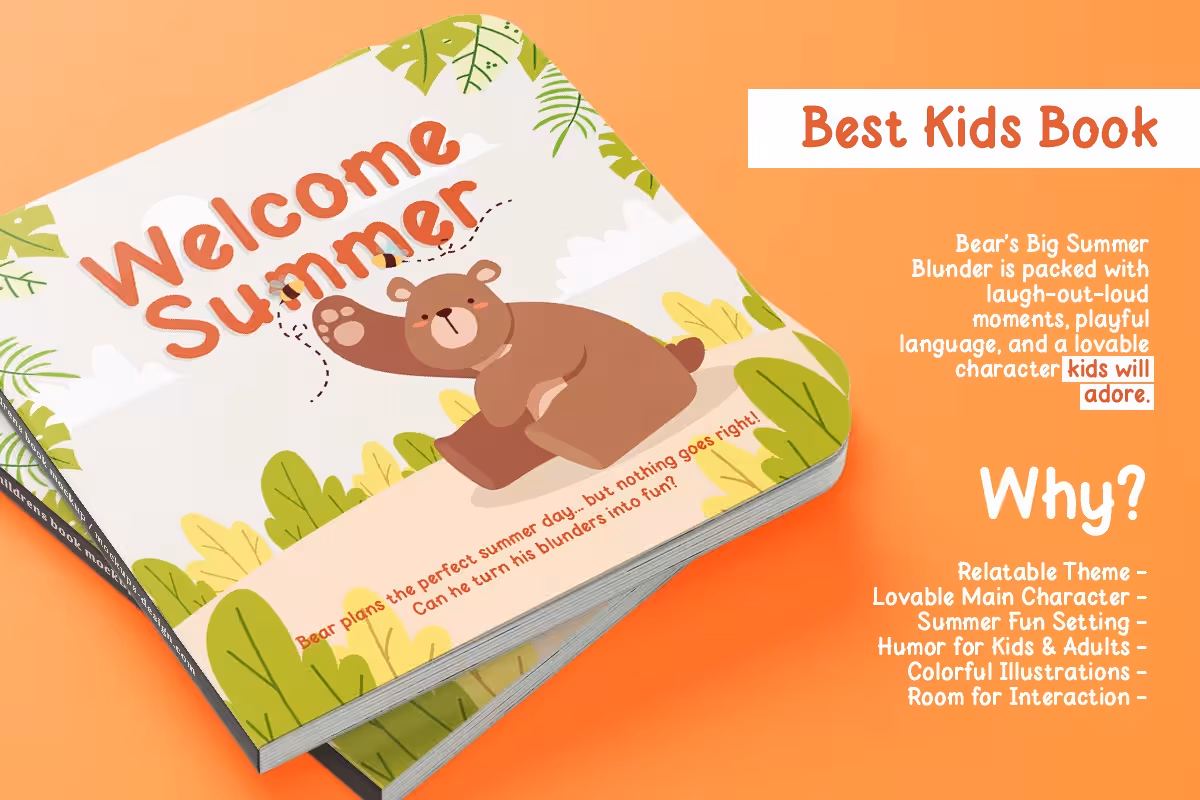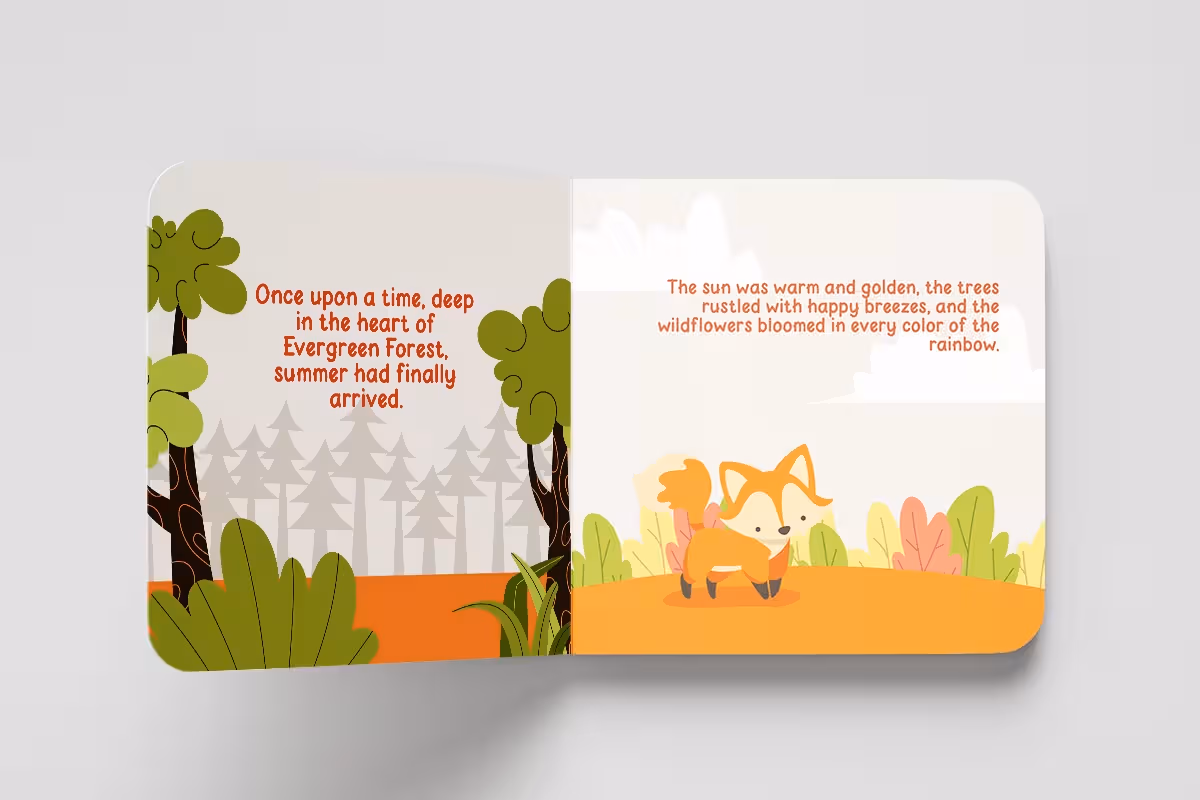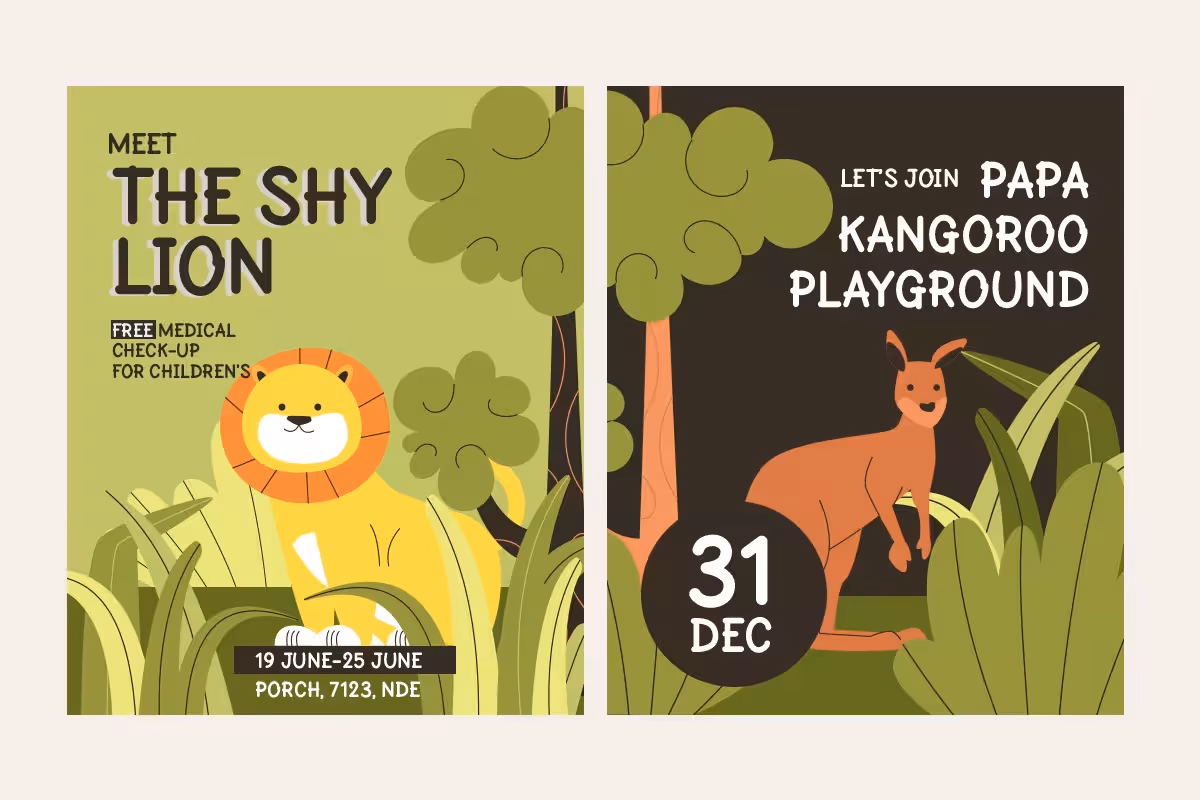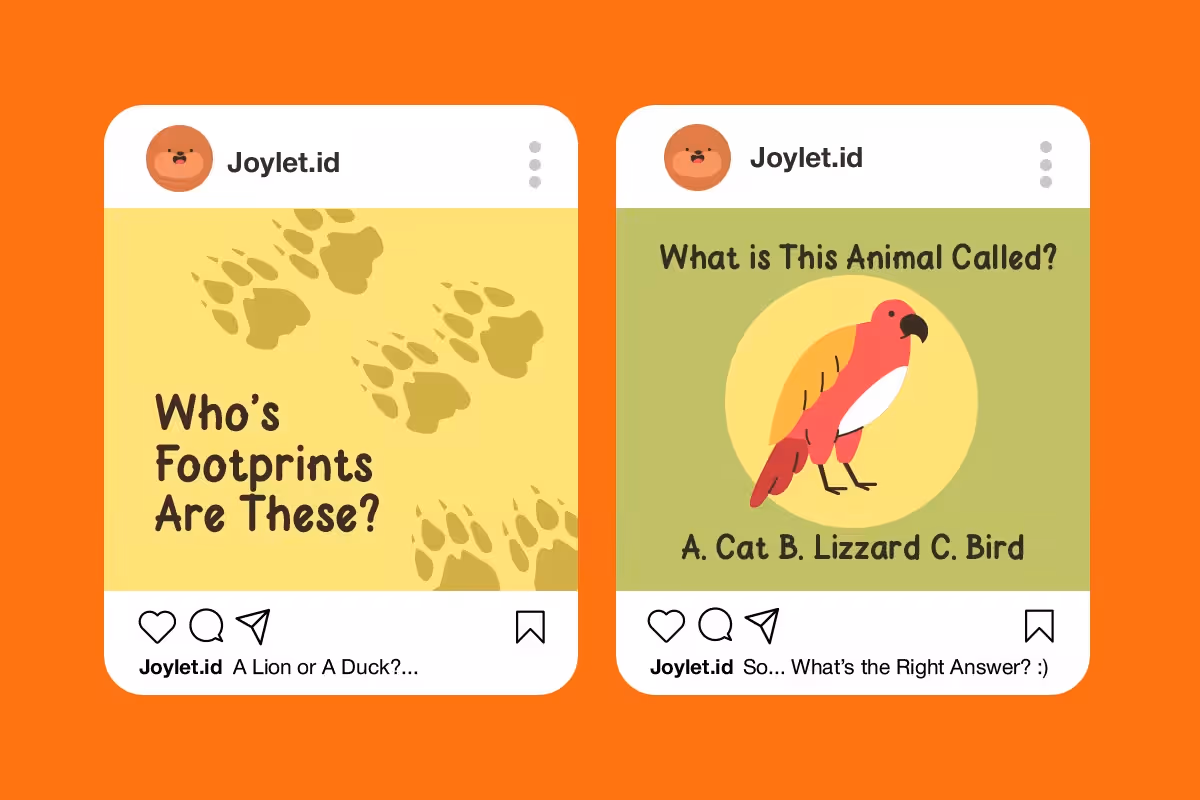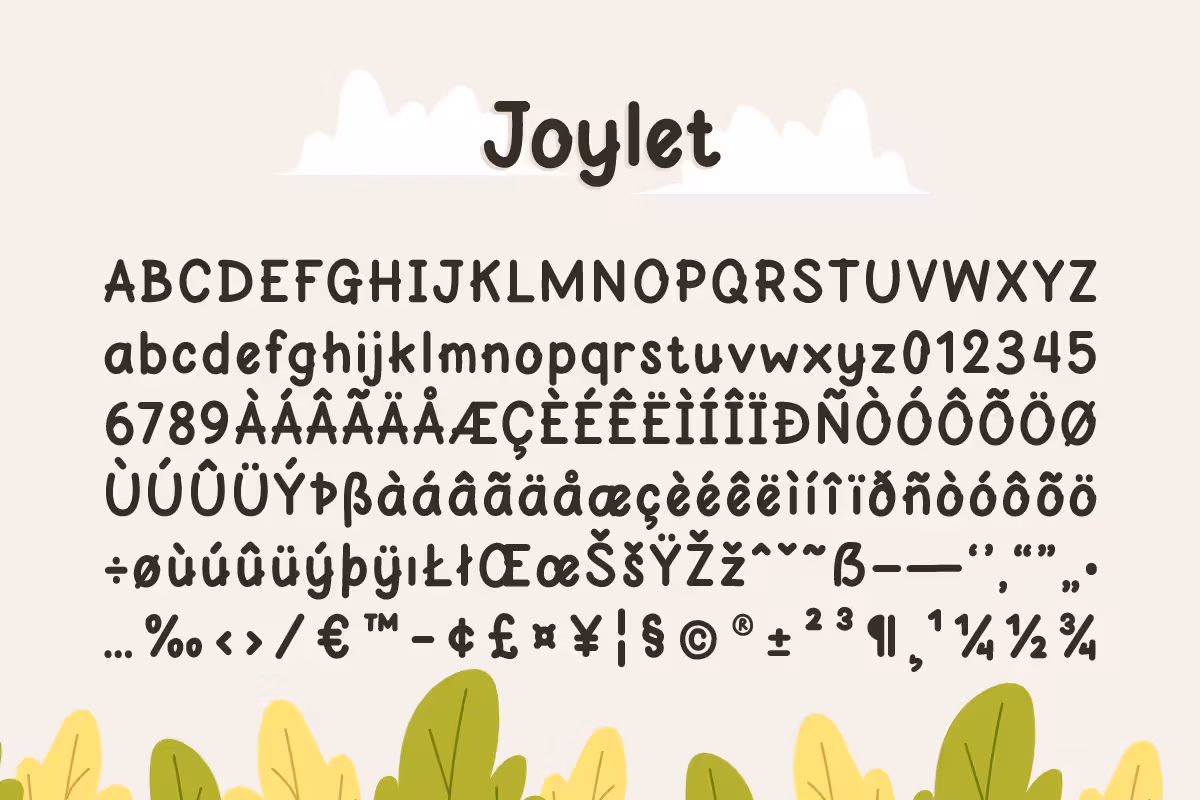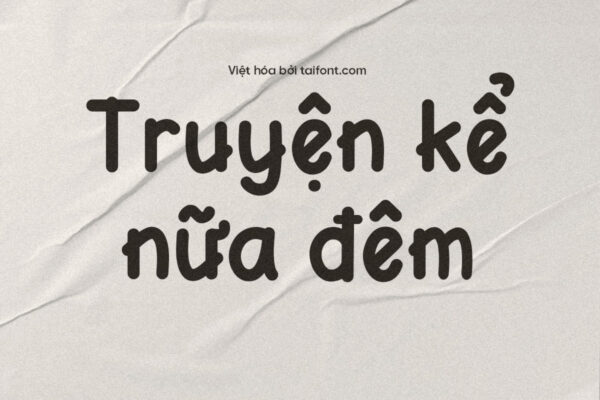
Giới thiệu về Font TF Joylet Việt hóa
TF Joylet Việt hóa là một font chữ nổi bật với thiết kế tròn trịa, đáng yêu và đầy ắp sự vui tươi, lý tưởng để mang đến không khí hồn nhiên và sống động cho các ấn phẩm dành cho trẻ em. Font này gợi cảm giác như những nét vẽ tay ngộ nghĩnh, tạo nên sự gần gũi, ấm áp và rất thân thiện.
Với đặc điểm nổi bật là hình dáng tròn trịa, nét chữ mềm mại và tính dễ thương, Joylet là lựa chọn lý tưởng cho các thiết kế muốn truyền tải sự vui tươi, đáng yêu và sự gần gũi, đặc biệt là trong các lĩnh vực:
- Thiết kế truyện tranh cho trẻ em: Hoàn hảo cho các đoạn hội thoại, lời dẫn chuyện, tiêu đề, hoặc chú thích trong truyện tranh, truyện thiếu nhi. Font này giúp tạo không khí vui nhộn, ngộ nghĩnh và thân thiện, thu hút sự chú ý và khuyến khích trẻ em đọc sách.
- Thiết kế đồ dùng học tập: Lý tưởng cho các nhãn vở, bút, hoặc các dụng cụ học tập khác, làm cho chúng trở nên đáng yêu và hấp dẫn hơn với các bé.
- Thiết kế bao bì sản phẩm (hướng trẻ em): Phù hợp cho bao bì các sản phẩm sữa, đồ uống, bánh kẹo hoặc đồ dùng cá nhân dành cho trẻ em, giúp sản phẩm trở nên thu hút và dễ nhận diện.
Với TF Joylet Việt hóa, bạn có thể dễ dàng thổi hồn vui tươi, đáng yêu và sự tươi mới vào các thiết kế, tạo ra những sản phẩm không chỉ đẹp mắt mà còn đầy cảm xúc và sức hút, đặc biệt hiệu quả cho các dự án dành cho trẻ em.
Font Việt hóa TF Joylet – Phong chữ thiết kế truyện tranh